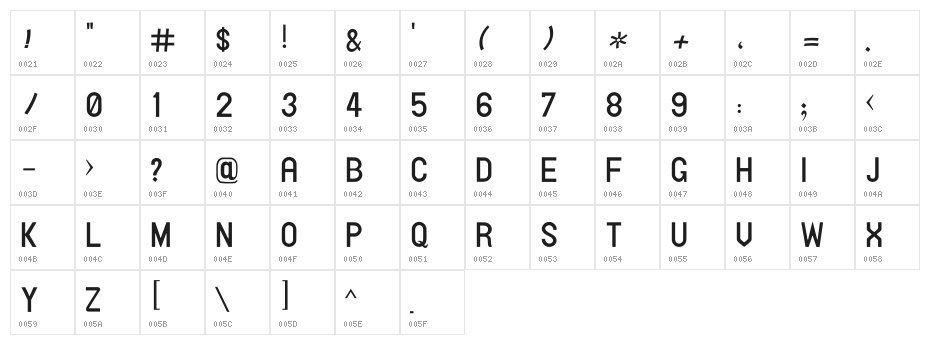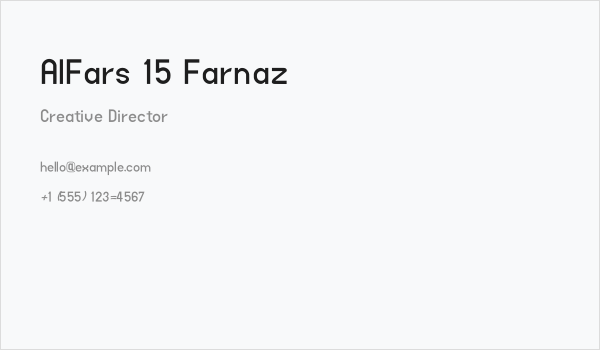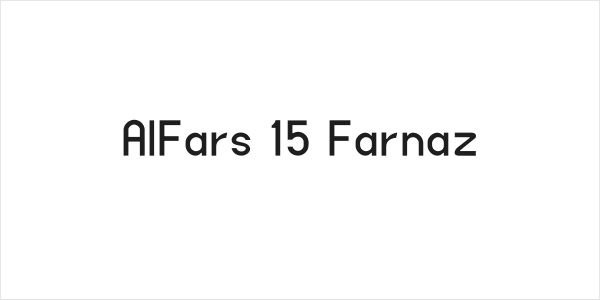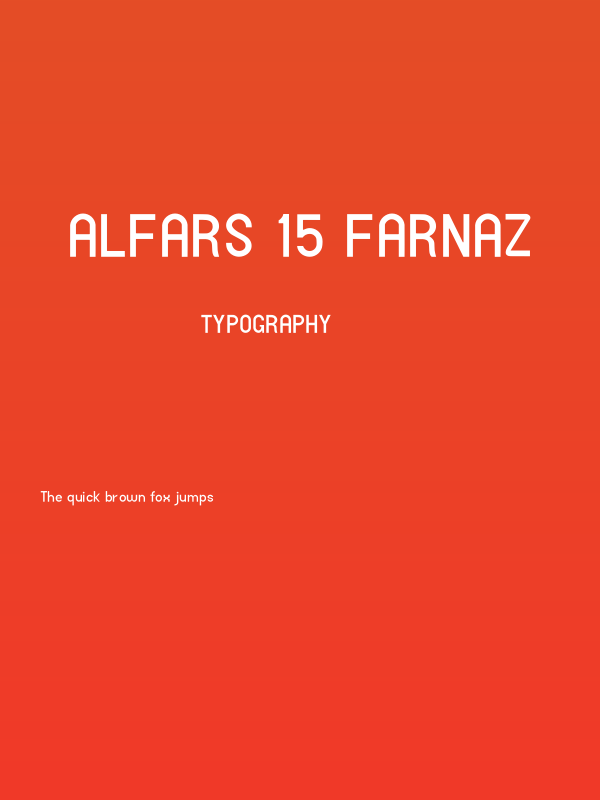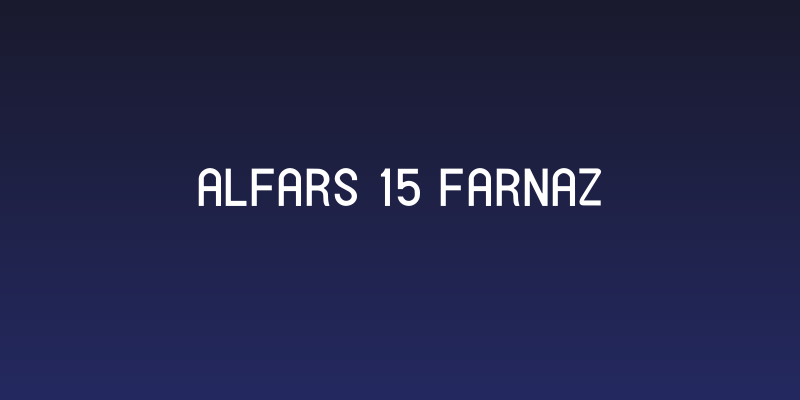
AlFars 15 Farnaz Font
| Anwendungsfall | Headlines, Logos, Web design |
| Vorgeschlagene Projekte | Ideal for branding, web design, advertising, and editorial layouts where clarity and modernity are essential. |